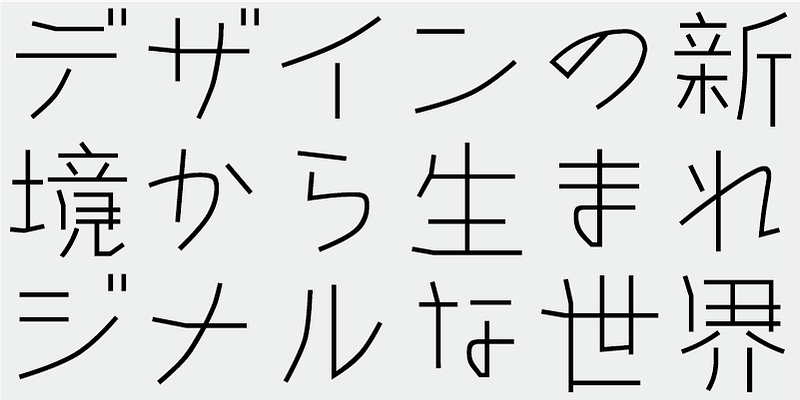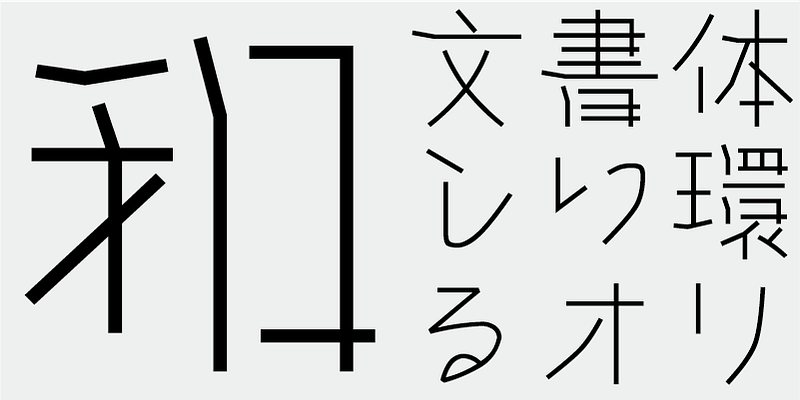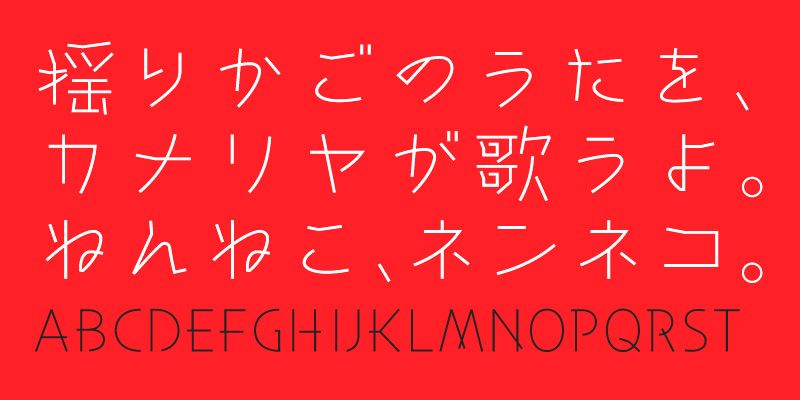
Diese Schriftart vermittelt einen linearen Eindruck wie ein Holzmosaik. Dieses altmodische Design wirkt immer noch neu und märchenhaft. Zeichen können in horizontaler und vertikaler Richtung frei angeordnet werden. Damit eignet sie sich für Display-Zwecke ebenso wie für Texte in Bilder- und Kinderbüchern.
Diese Schrift umfasst 1.000 wichtige Kanji-Zeichen, die aus einer von Zeitungen, Verlagen und Forschungsinstituten für Linguistik erstellten Tabelle der häufigsten Zeichen ausgewählt wurden, plus 206 Kana-Zeichen und Interpunktion.
In der heutigen japanischen Schriftproduktion gelten die 7.000 Zeichen des JIS-Standards als unabdingbar. Aber brauchen alle Schriften wirklich 7.000 Zeichen? Im Zeitalter des Fotosatzes wurden weit weniger Zeichen benötigt. FONT1000, eine Gruppe unabhängiger Schriftdesigner, ging von dieser einfachen Frage aus. Wir haben die mindestens 1.000 (ideografischen) Kanji-Zeichen ausgewählt, die für den Satz in Japanisch erforderlich sind, und aktiv Schriften und Schriftbilder dafür entworfen. Dieser 1000-Kanji-Zeichensatz wurde unter Verwendung von Zeichenhäufigkeitsdaten ausgewählt, die u. a. von Zeitungsunternehmen, Verlagen und Sprachforschungsinstituten zusammengestellt wurden, und enthält auch Kana-Silbenzeichen und Satzzeichen. FONT1000 begann 2001 mit 25 Designern und 25 Schriften. Heute haben wir 130 Schriften und sind auf fast 40 Mitglieder angewachsen, sodass wir an Schriften mit mehr Zeichen arbeiten können.